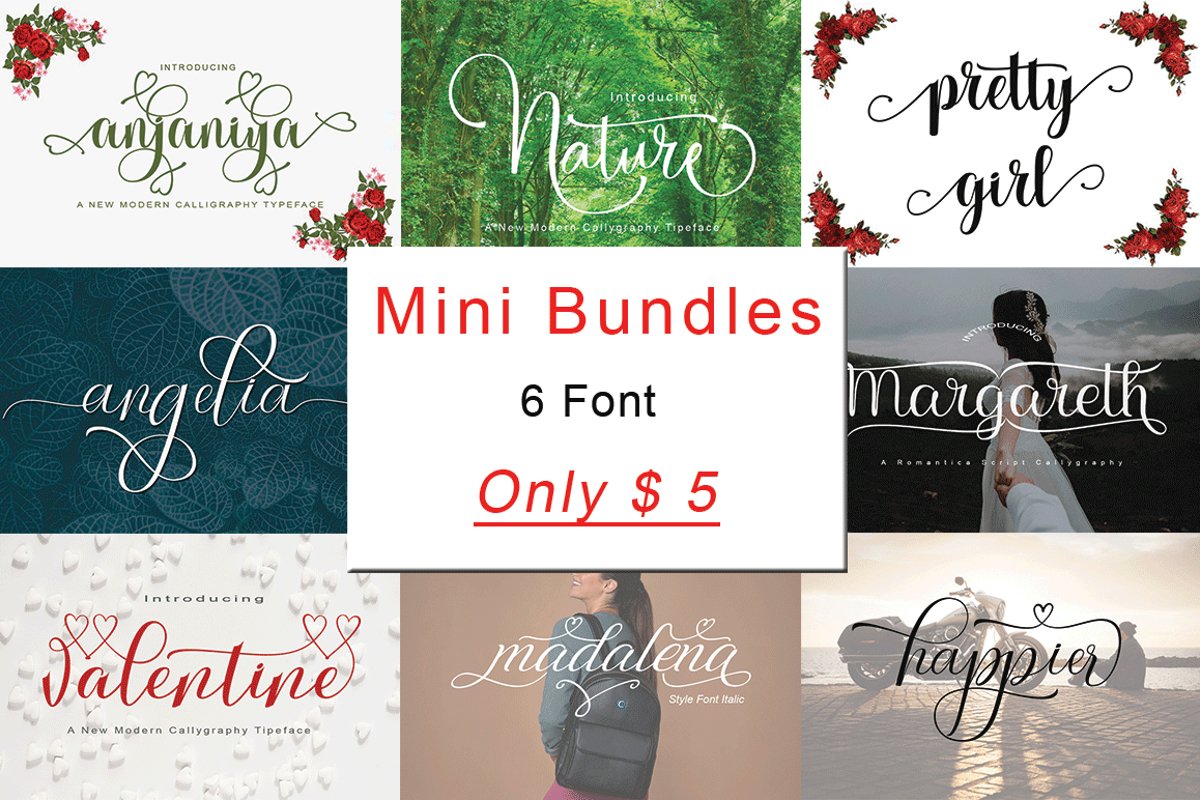
MINI BUNDLES
Nature
MargarethItalic
valentine
Angelia
Margareth
Anjaniya
MEMPERKENALKAN MINI BUNDLES
Bundel ini mencakup beberapa font terlaris, dengan ratusan mesin terbang, termasuk alternatif, ligatur, swash, swash terpisah, alternatif kontekstual dan dukungan bahasa internasional. yang dapat diakses menggunakan program OpenType yang cerdas seperti Adobe Illustrator, Adobe InDesign, CorelDraw X6-X7, Microsoft Word 2010 atau versi yang lebih baru.
Semua font cocok untuk undangan pernikahan, promosi media sosial, judul, tanda tangan, logo, t-shirt, kop surat, papan nama, label, buletin, branding, pos, logo, blog, kop surat, merchandise, papan nama, berita, poster, lencana , dll.